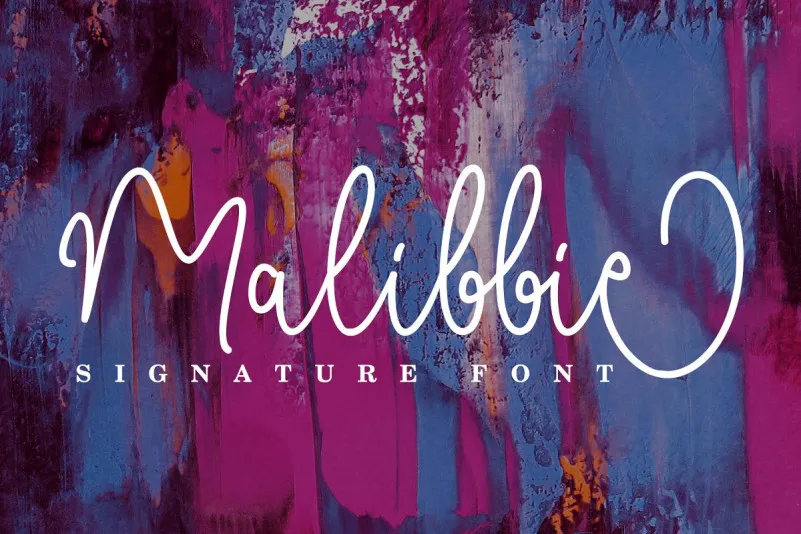
Malibbie Signature Font – Fonte Grátis
Malibbie Signature Font
Escolhendo uma fonte para seu próximo projeto? Opa! A M.0Type introduziu a Malibbie Signature Font, que certamente vai revolucionar sua paleta de fontes. Essa é uma fonte script contemporânea com um toque elegante e sofisticado, que traz naturalidade com muitos ligaduras adicionais. Introduzimos a Malibbie Signature Font! Desenvolvida pela M.0Type, essa fonte não apenas é visualmente atraente, mas também possui uma textura natural que torna-a ideal para diversos tipos de projetos gráficos. Seja um logotipo elegante e sofisticado ou um álbum de fotos criativo com toques de personalidade, a Malibbie Signature Font se destaca pelo seu uso versátil, legível e fácil de usar. Suas opções vão desde o design da marca até os cards de negócios, passando por citações, selos e até mesmo as capas de álbuns. Obrigado à M.0Type pela oferta desta fonte impecável para ajudar a tornar seus projetos ainda mais notáveis.